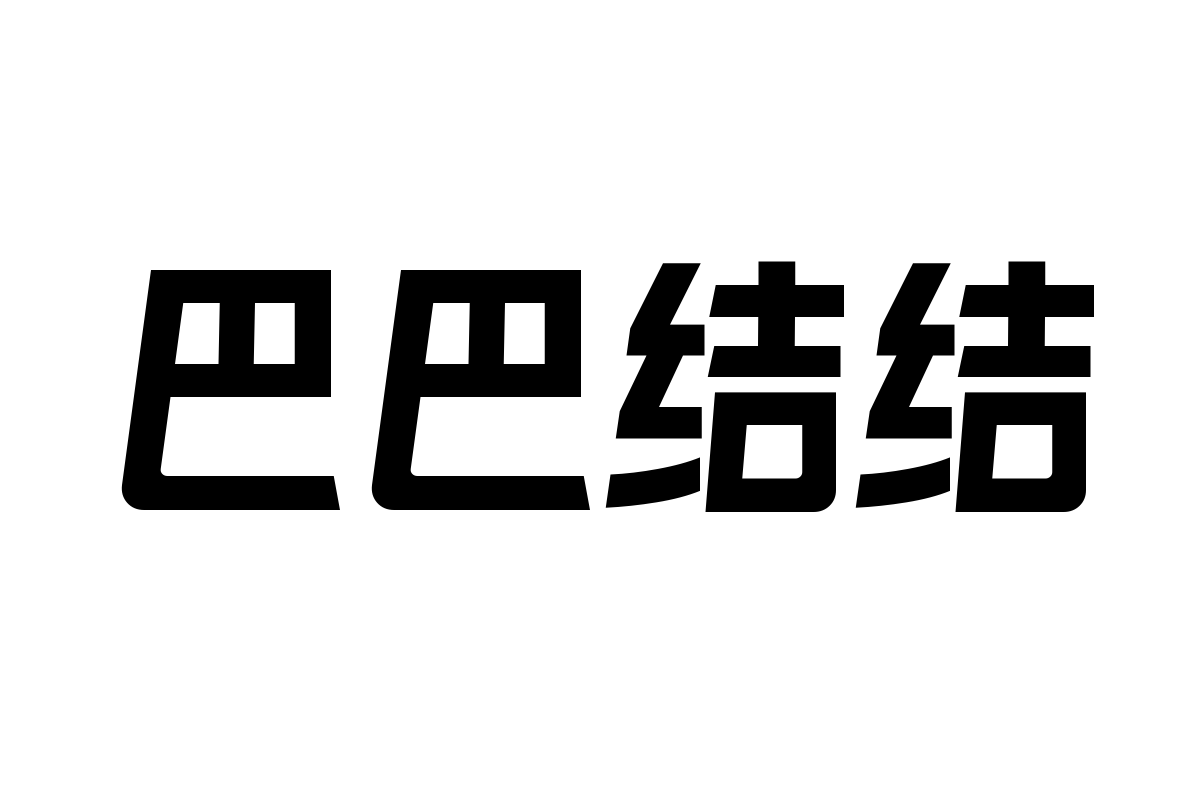
锐字太空筑梦黑大黑是一款现代简约风格的中文字体,具有独特的设计和艺术感。它的笔画流畅、清晰,给人一种轻松、愉悦的感觉。这款字体适用于各种设计场景,如广告、海报、包装、网页等,能够很好地传达出品牌的形象和风格。
锐字太空筑梦黑大黑的字形结构紧凑,线条简洁有力,既保留了传统汉字的韵味,又融入了现代设计的元素。它的字体大小适中,易于阅读,适合用于需要突出显示的文字内容。此外,这款字体还具有一定的可扩展性,可以根据需要进行个性化定制。
总的来说,锐字太空筑梦黑大黑是一款非常实用的中文字体,适合用于各种需要强调文字设计的场景。无论是企业品牌、广告宣传还是个人作品,都可以选择这款字体来提升视觉效果和传达信息。